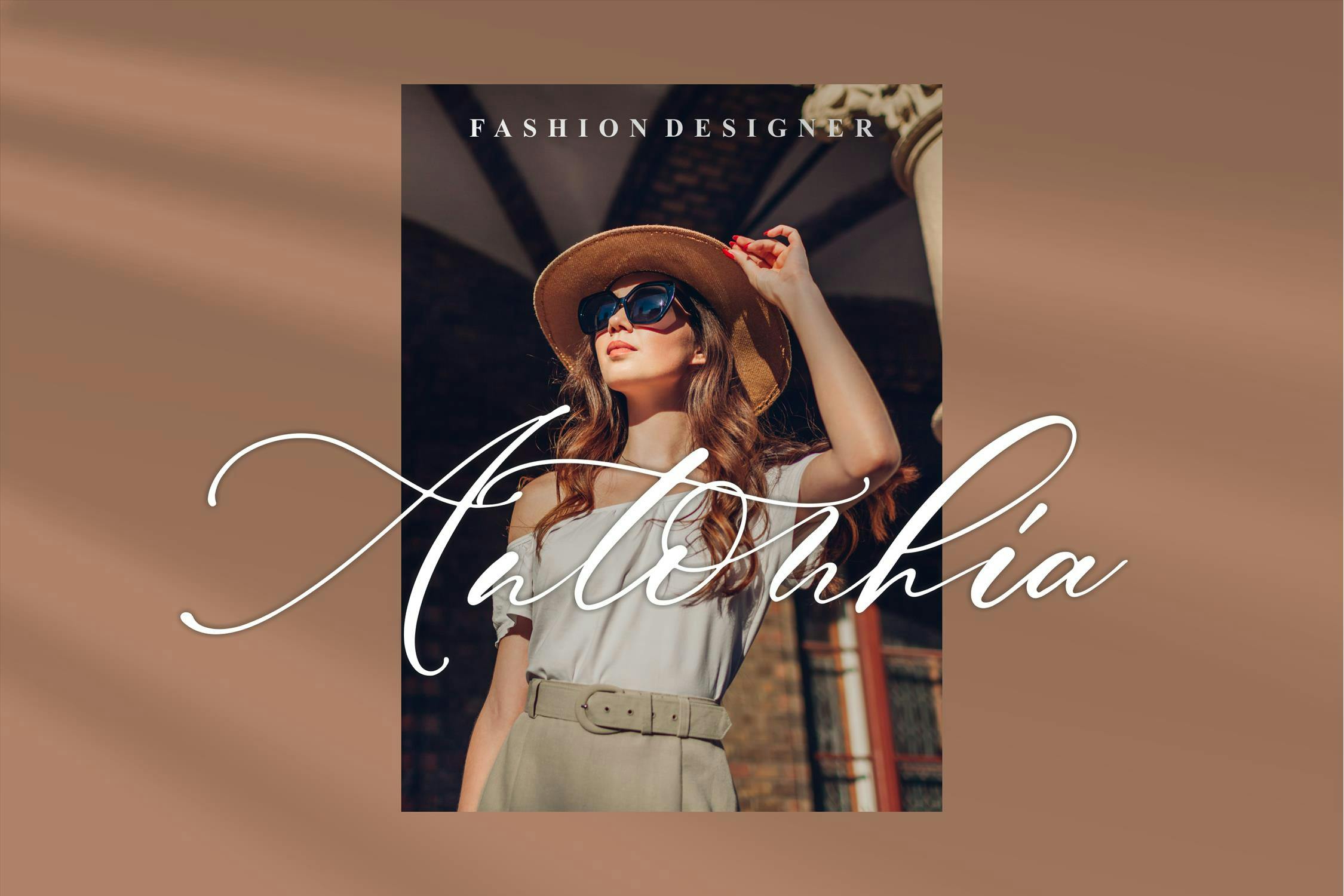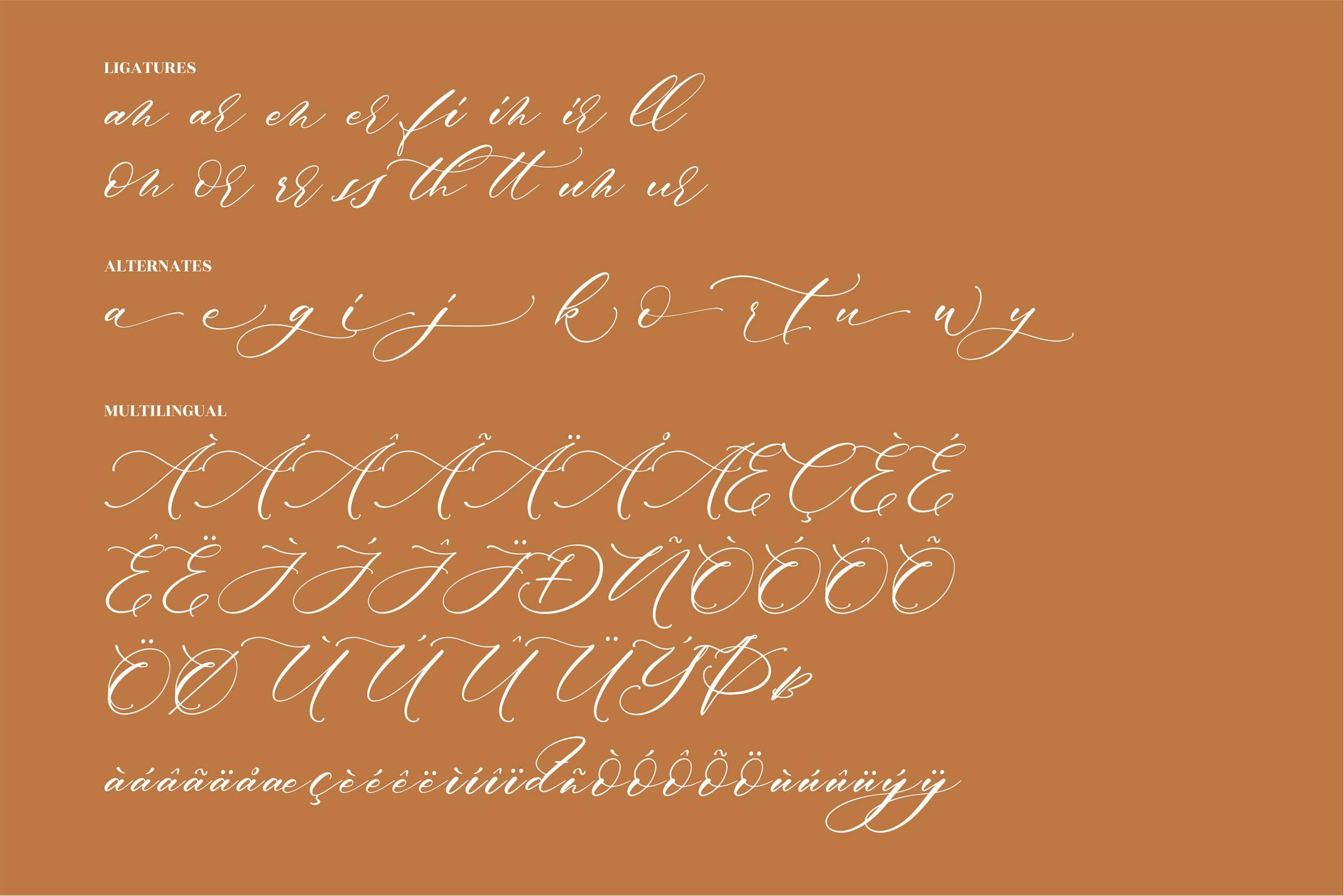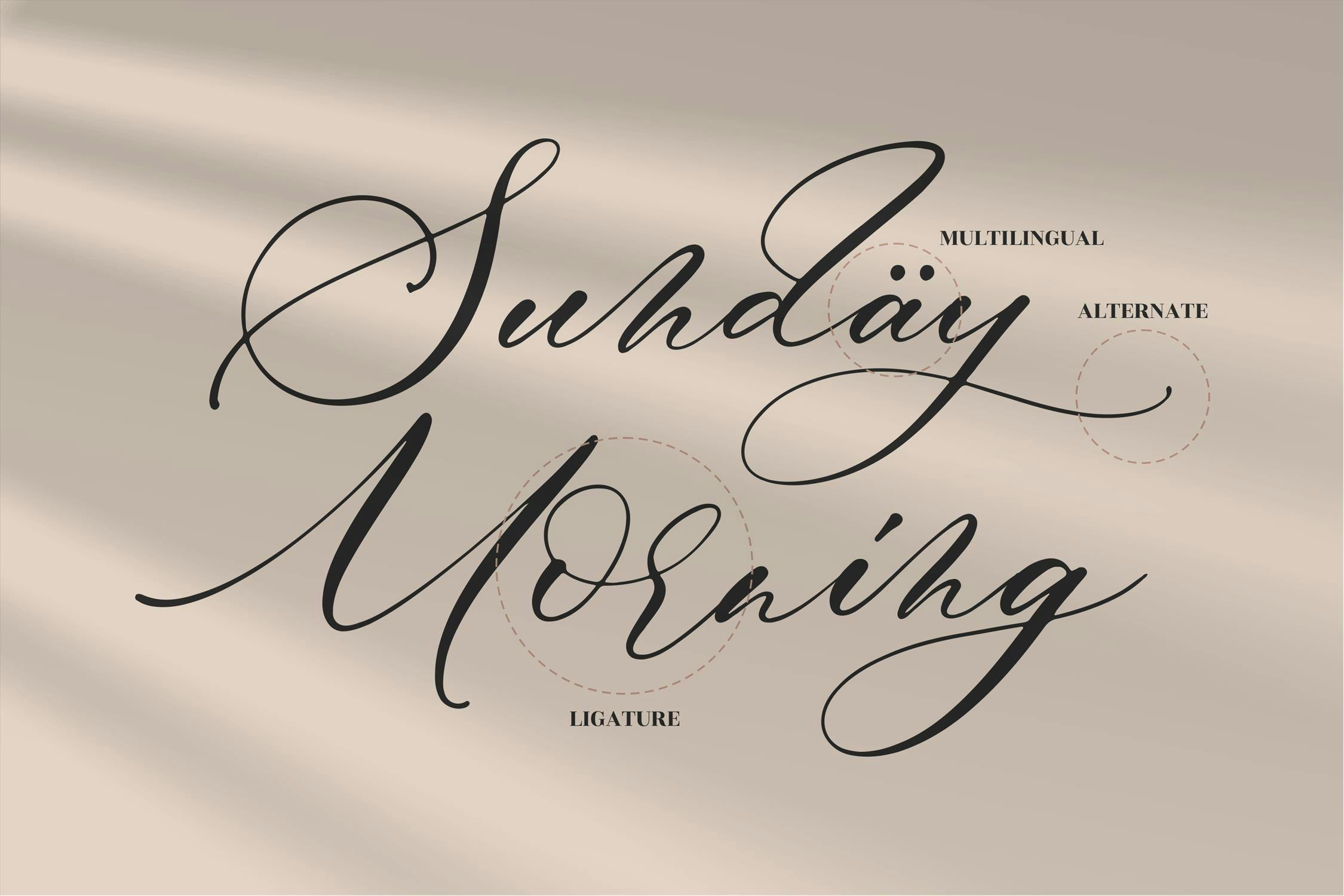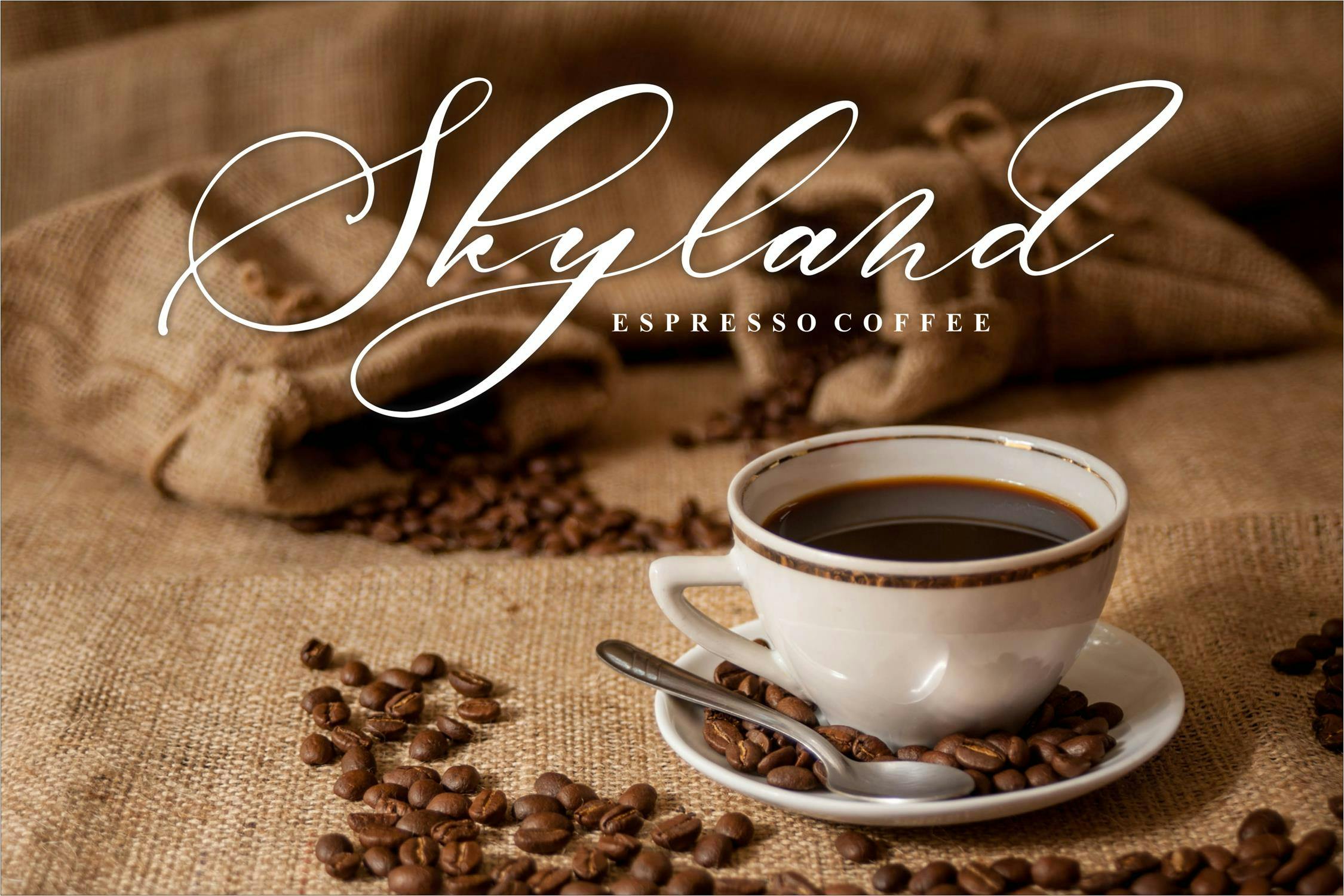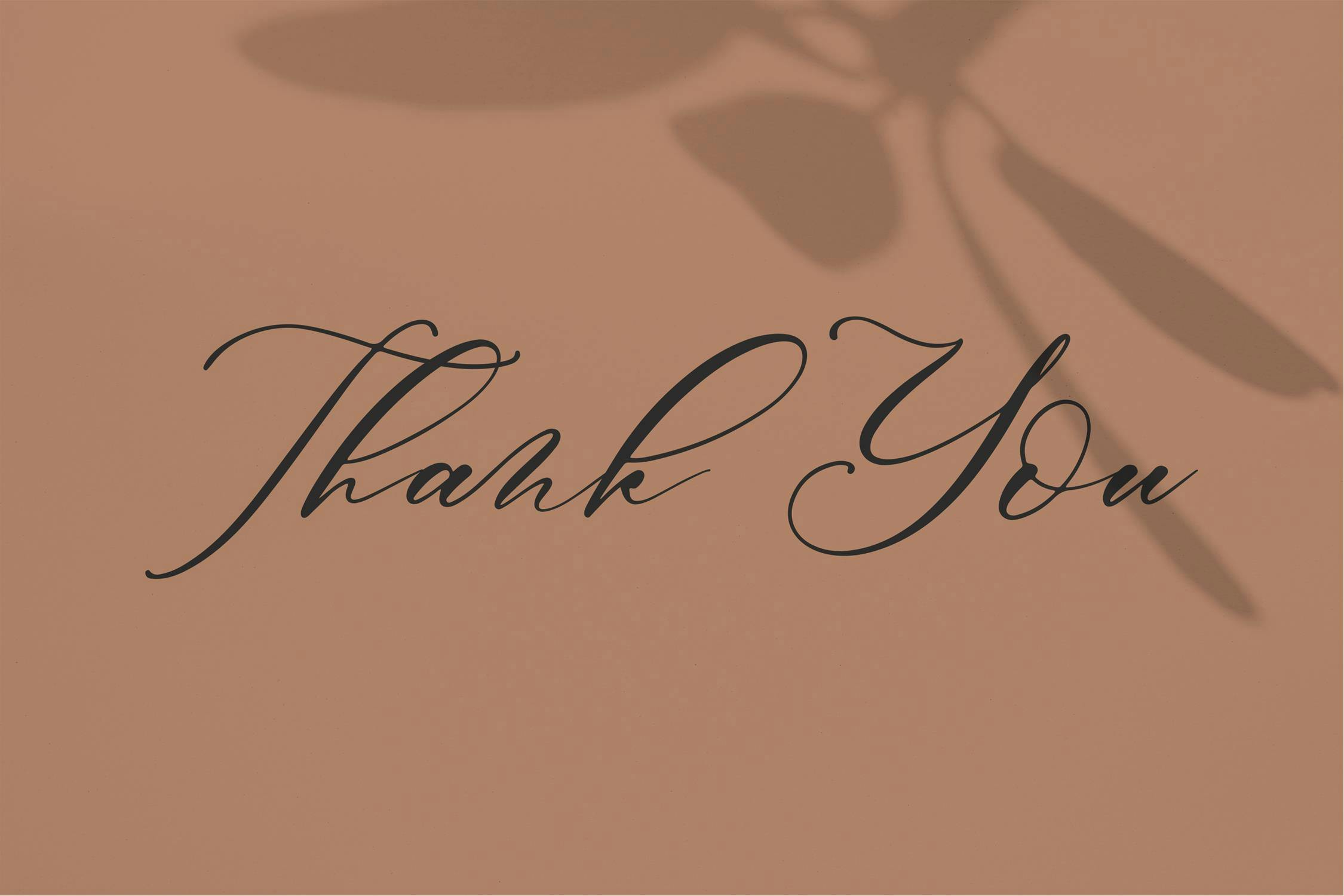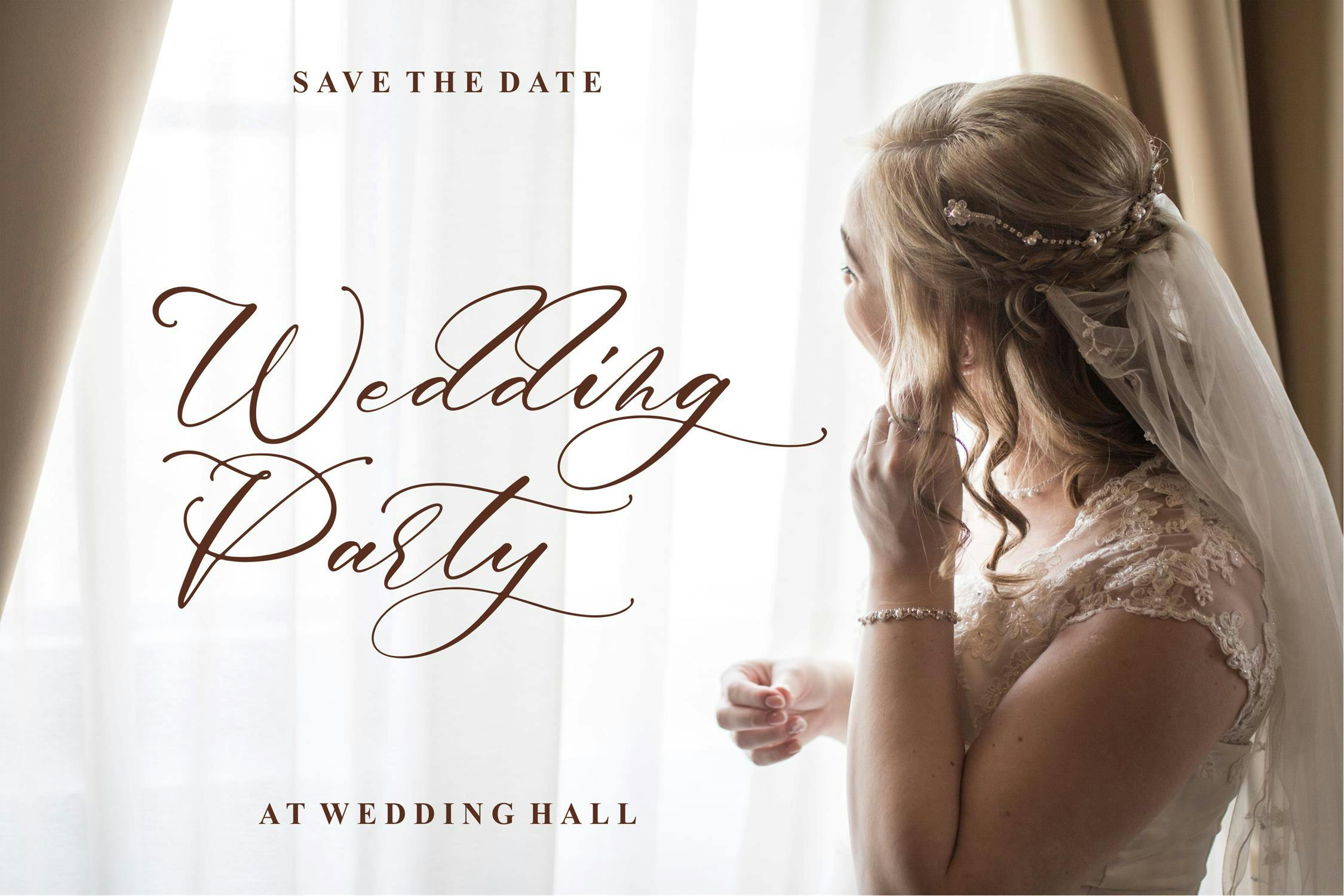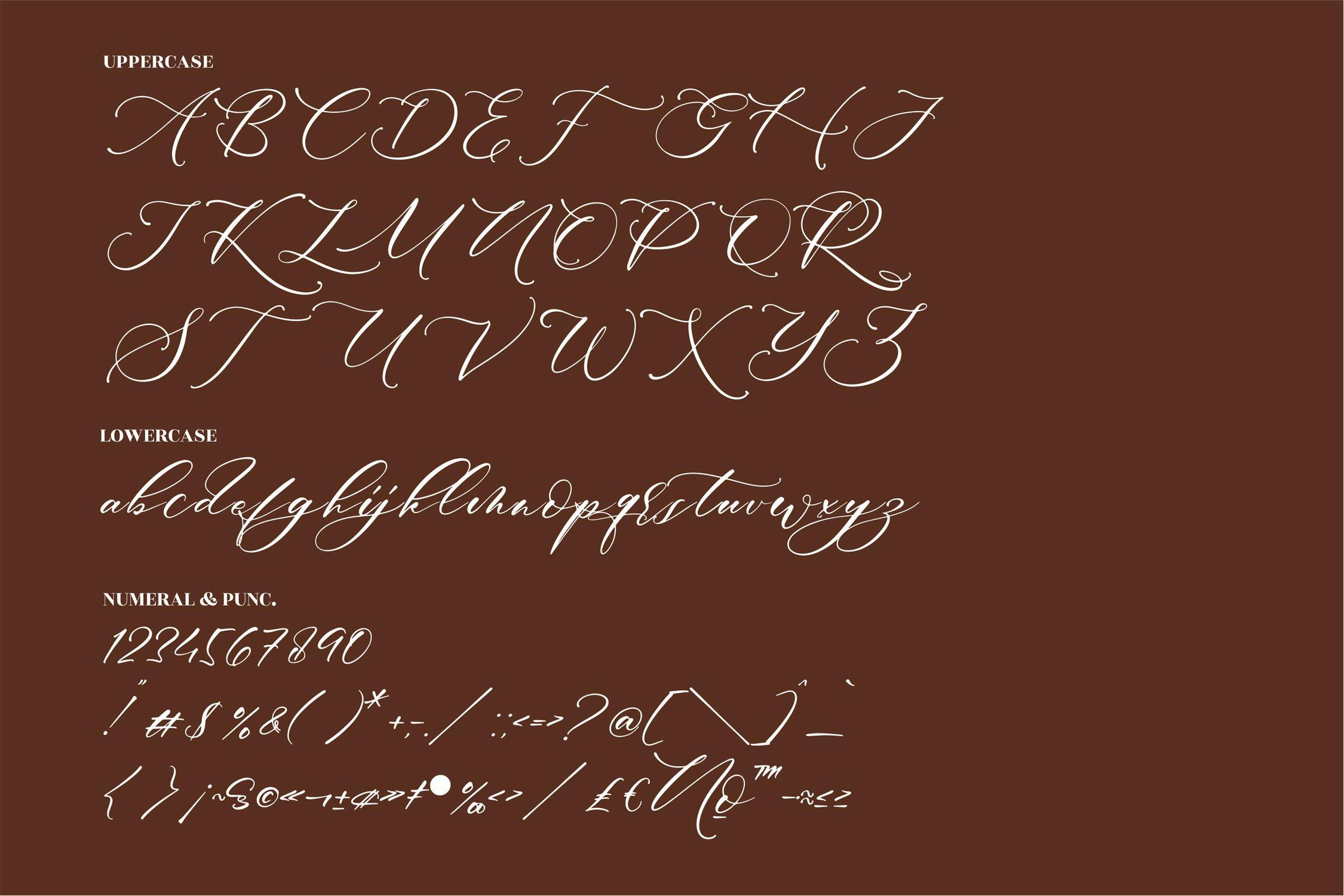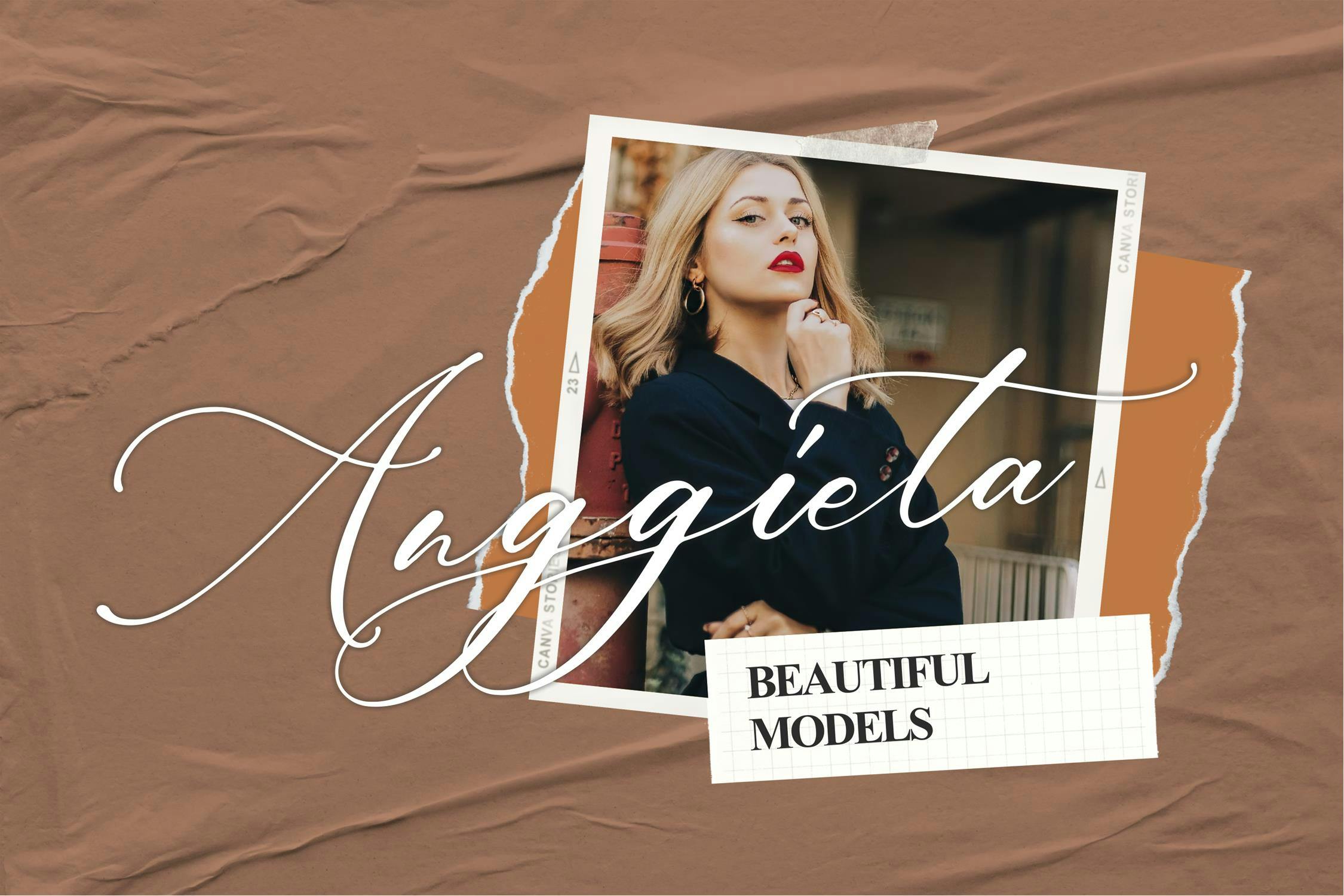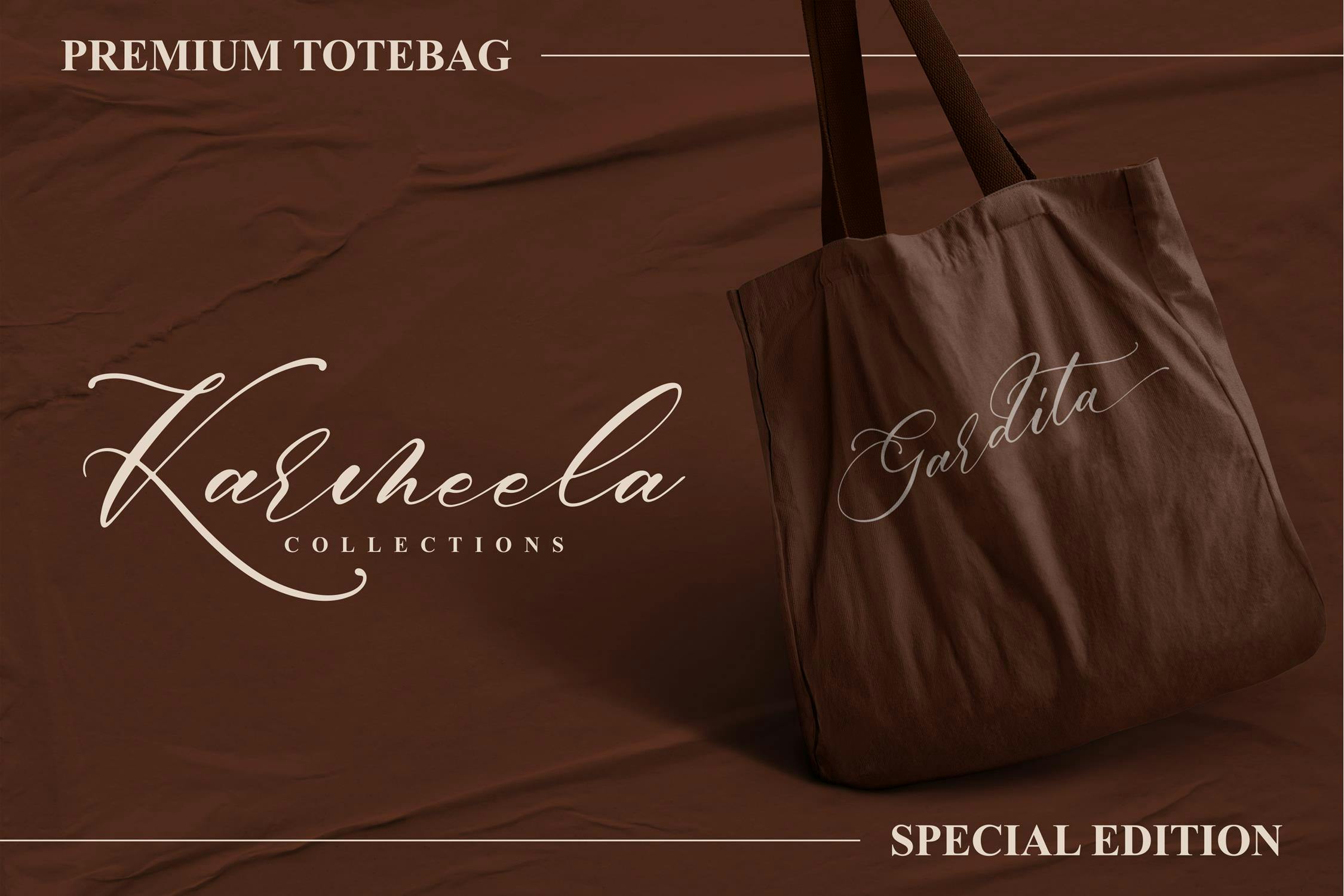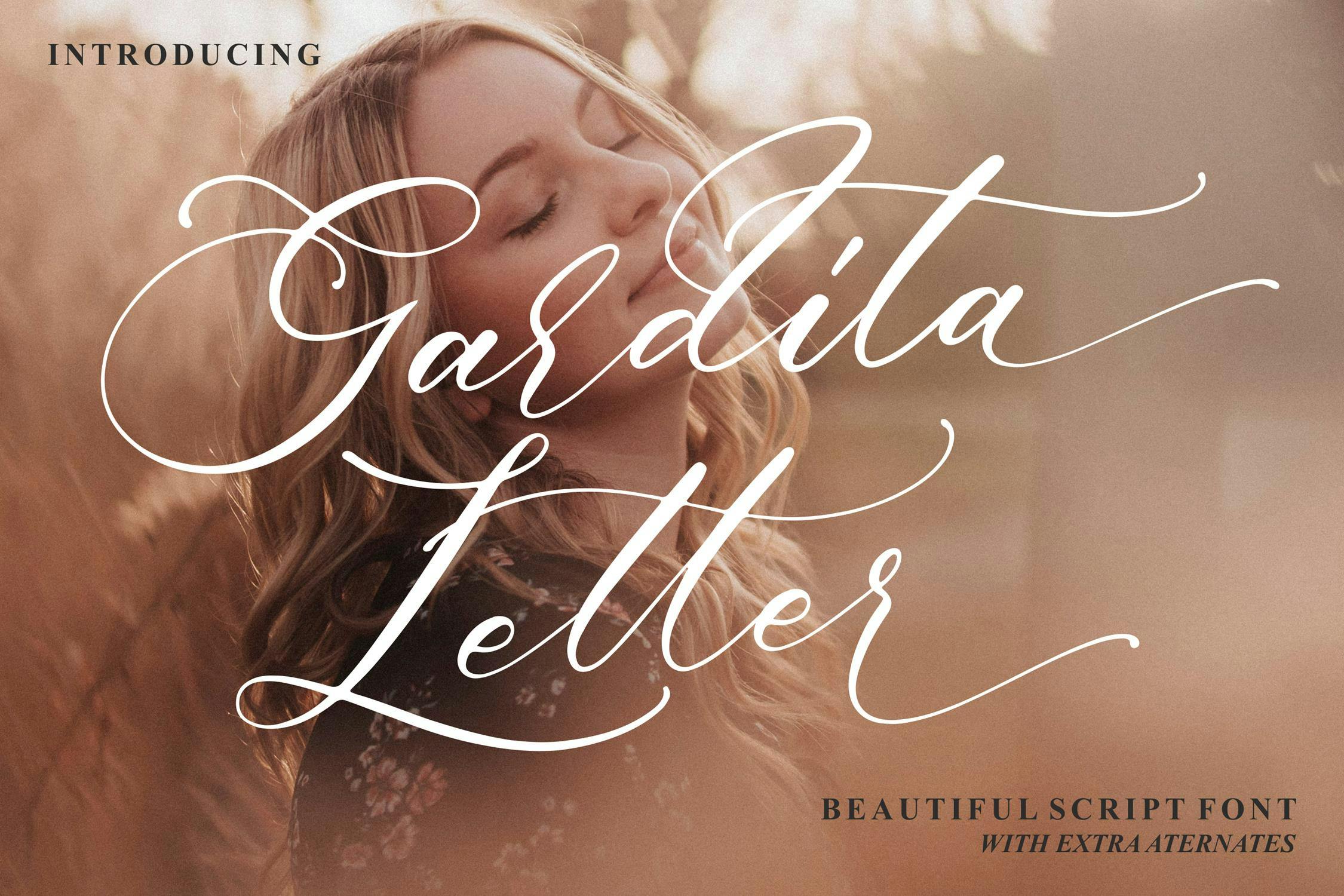
سلام خانمها و آقایان، این یکی از فونتهای ماست که به خوبی میتواند محصولات خلاقانه دیجیتال و چاپی شما را تکمیل کند.
این فونت برای طراحی پوسترها، پستهای شبکههای اجتماعی، برندینگ، پروژههای شخصی و غیره بسیار مناسب است.